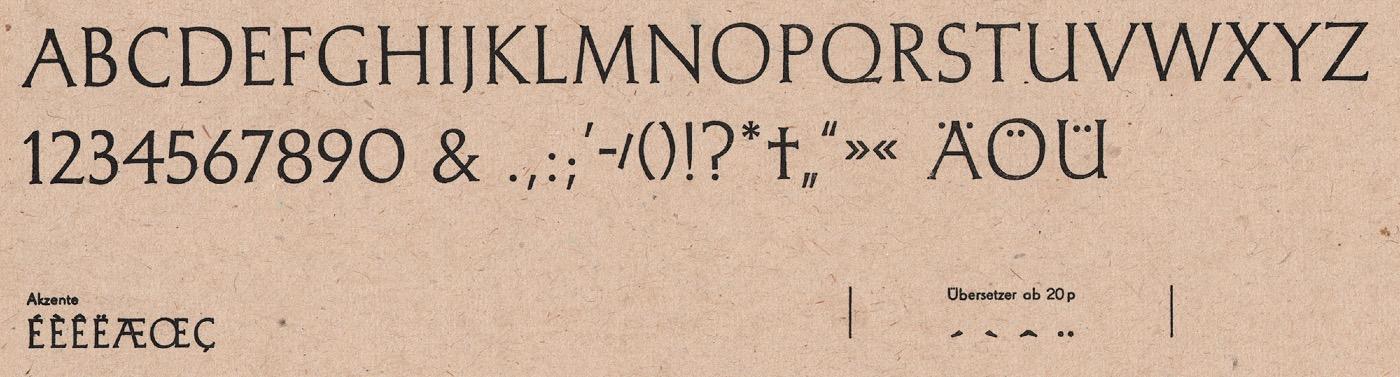
Font-Wiki: Roesner-Versalien
• 1960
• Serifen:
• serif
• Antiqua humanistisch
Roesner-Versalien, benannt nach ihrem Schriftgestalter Wolfgang Roesner, ist eine Großbuchstabenschrift im Duktus einer Capitalis Monumentalis. Die Schrift erschien 1960 als Bleisatzschrift beim VEB Typoart.